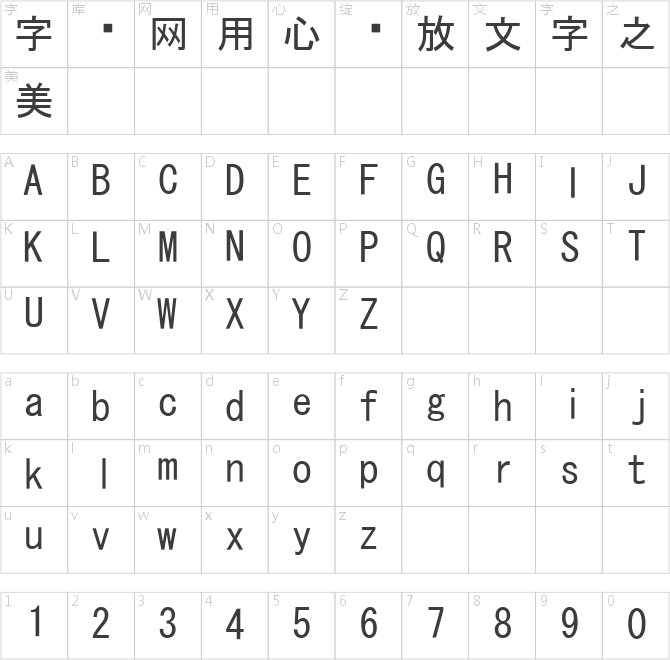
真宗圣典黑體
真宗圣典黑體介紹
真宗圣典黑體字體下載ShinshuSeitenGothic真宗聖典ゴシック
真宗圣典楷書是日本“凈土真宗圣典”系列字體的其中一款。這個字體是為了將日本佛教「凈土真宗派」的各大經典電子化而開發的字體,字體字形還原原書,頗具風韻。
真宗圣典黑體字體ShinshuSeitenGothic真宗聖典ゴシック字庫是一款讓人賞心悅目、百看不厭的中文字體,適合各類廣告和產品包裝設計應用,字體大小4.33MB,格式為ttf字體,上傳用戶是曉語無聲,作者/版權方為ARIKUNI Tomomitsu